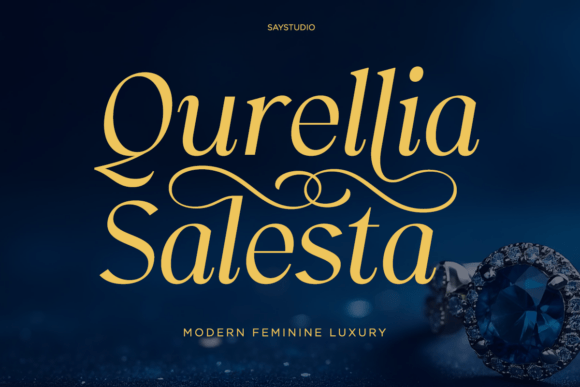
Qurellia Salesta
قد يكون العثور على عناصر التصميم المناسبة أمرًا صعبًا، ولكن Qurellia Salesta يقدم مجموعة استثنائية ترتقي بعملك على الفور.
سواء كنت تقوم بإنشاء منتجات الطباعة عند الطلب أو دعوات الزفاف أو رسومات وسائل التواصل الاجتماعي، فإن Qurellia Salesta هو الخيار المثالي.